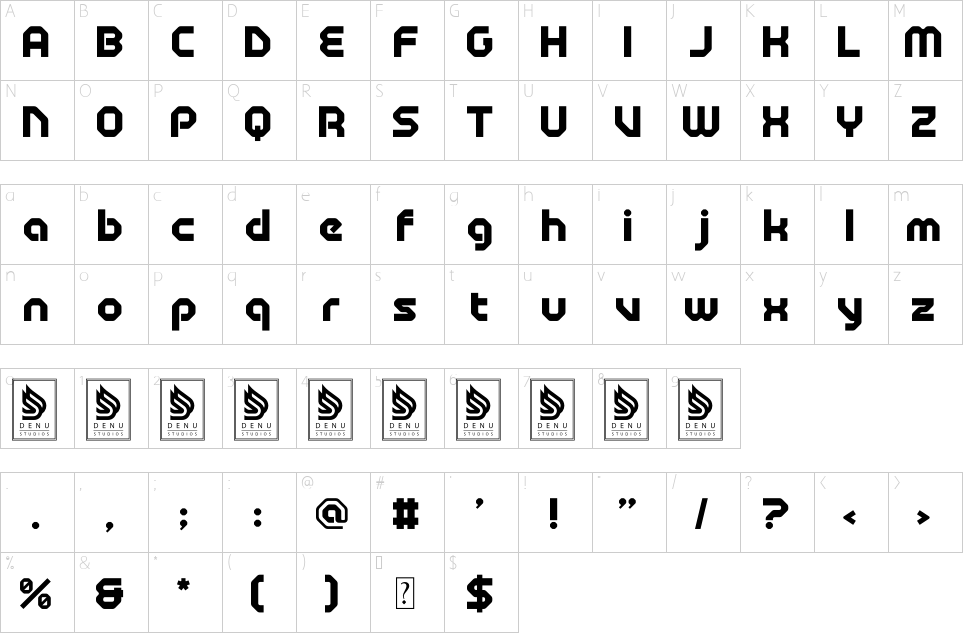
A Arbedo Font é uma grata surpresa para designers e amantes da arte digital. Desenhada pela Gracetypestudio, esta fonte está disponível gratuitamente tanto para Windows quanto para Mac. Seu design elegante e natural foi criado para complementar uma variedade de projetos digitais, desde sites e designs gráficos até criações digitais de ilustração. Com uma aparência suave e confortável, a Arbedo Font é perfeita para quem busca uma solução de fonte para projetos que exigem uma presença atraente e profissional. Com seu download único de 352 vezes, é evidente que muitos designers já se renderam ao seu encanto. Navegar através do design de fontes digitais pode ser desafiador, mas a Arbedo Font é uma excelente escolha para ajudar a tornar seu trabalho mais atraente e profissional.